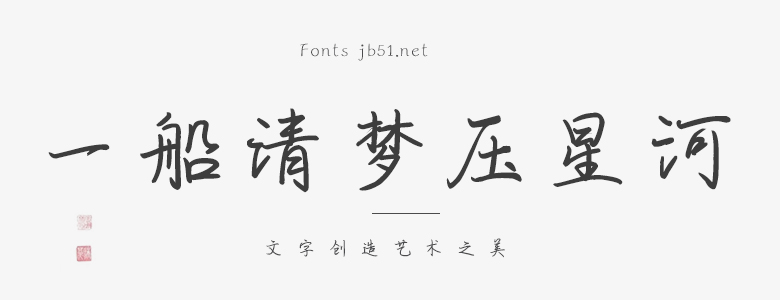
一船清夢(mèng)壓星河是一款獨(dú)特且富有藝術(shù)感的字體,它的設(shè)計(jì)靈感來(lái)源于夜晚星空下的長(zhǎng)江航行。字體的每一個(gè)筆畫(huà)都仿佛是一幅夜空的畫(huà)卷,充滿了神秘與夢(mèng)幻的氣息。 一船清夢(mèng)壓星河的筆畫(huà)設(shè)計(jì)巧妙,通過(guò)優(yōu)雅的曲線和銳利的角度對(duì)比,形成了獨(dú)特的視覺(jué)效果。這款字體的字重適中,既不會(huì)過(guò)于沉重,也不會(huì)過(guò)于輕飄,能夠適應(yīng)多種不同的排版需求。 字體中的“一”字就像一艘船,穩(wěn)穩(wěn)地航行在星河中,帶著夢(mèng)想與希望。“清”字則仿佛是夜晚江面上的一縷清風(fēng),給人帶來(lái)寧?kù)o與舒適。“夢(mèng)”字又像是一個(gè)星空下的夢(mèng)境,充滿了奇幻與神秘。而“壓”字則像是在星河的壓力下,保持著堅(jiān)韌與決心。 整款字體設(shè)計(jì)簡(jiǎn)潔大方,同時(shí)又充滿了詩(shī)意和情感。無(wú)論是用于書(shū)籍的封面設(shè)計(jì)、雜志的內(nèi)文排版,還是用于品牌標(biāo)識(shí)或個(gè)人作品的設(shè)計(jì),一船清夢(mèng)壓星河都能展現(xiàn)出其獨(dú)特的魅力。